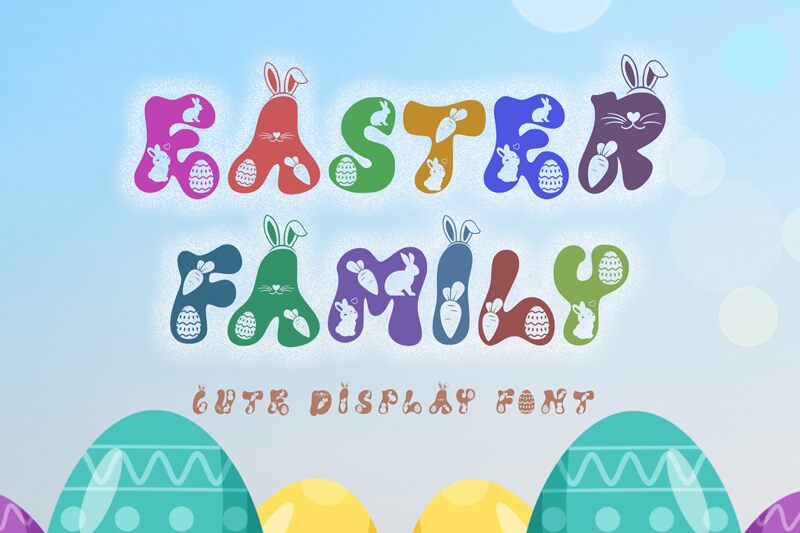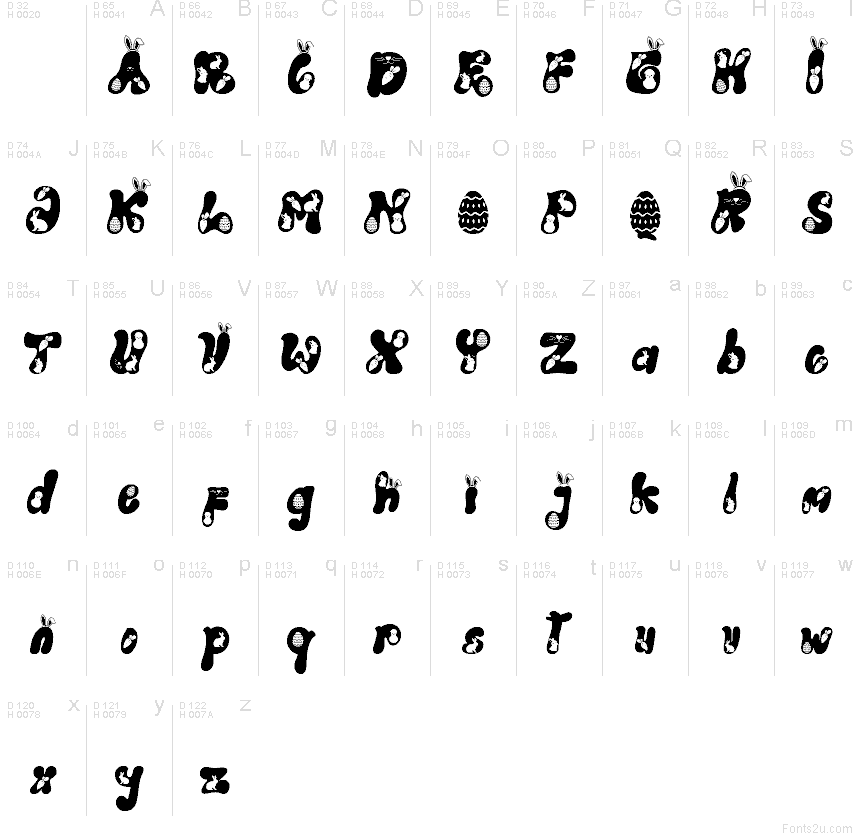
Easter Family
A Easter Family, da Yoga Letter, é uma fonte decorativa gratuita com temática de Páscoa. Suas formas arredondadas trazem pequenas figuras de coelhos, ovos com bolinhas e alguns detalhes em formato de coração. O motivo recorrente confere um visual artesanal e festivo, sem comprometer a leitura de cada caractere.
A Easter Family funciona muito bem em cartões de Páscoa, convites de festas primaveris, pôsteres sazonais, páginas de scrapbook e artes para redes sociais que precisam de um título temático. Esta fonte gratuita também é perfeita para etiquetas de padaria, tags de presente e embalagens artesanais, onde os detalhes divertidos de coelhos e ovos transmitem a mensagem festiva por conta própria.